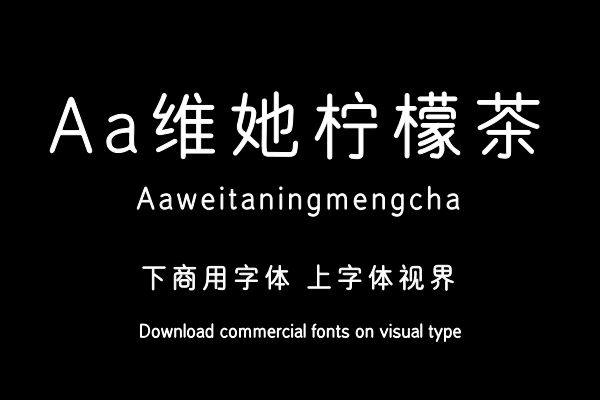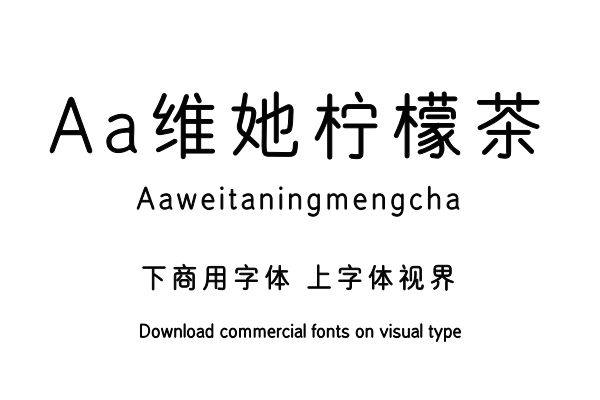
圆润而富童趣的可爱圆体。维他柠檬茶以常规黑体结构为基础,对字形、笔画细节进行再设计。结构纵向拉长,整体上保留了细黑出色的显示效果,笔画的圆角设计,使字体整体风格......购买须知:“下载服务费”与“字体VIP”所获得字体 仅用于个人非商用, 商用请联系付费授权。本字体为电脑用字,手机没有root权限不支持直接手机换字(手机如何root,请自行百度搜索教程)。购买前请先 了解清楚后再付款 ,字体为虚拟产品无法回收 一旦购买不支持退款。